时代真的是飞速的发展着,记得几年前还在讨论着90后,现在都已经是10后了,学生的思想越来越新朝,所以传统时代的文化已经不能满足这些年轻人的需求了,就连字体也是。现在的女生对自己的要求也越来越高,大家都纷纷研究着跟别人不一样的带有自己风格的字体,那么下面字体视界就为女孩们推荐几个适合女生练的硬笔字体吧。还有很多的字体可供大家选择,您可以到字体视界找一下哦!
首先推荐的这个义启雅俗共赏字体特别的细,小编认为细的字看起来比较的干净,小编认为女生写字最重要的就是要洗,尽量的小这样看起来特别的干净,秀气。这款字体基本上就是为女生定做的,而且她比较的方正,字与字之间的间隔显得也比较大,所以这是一款适合女生练的硬笔字体。
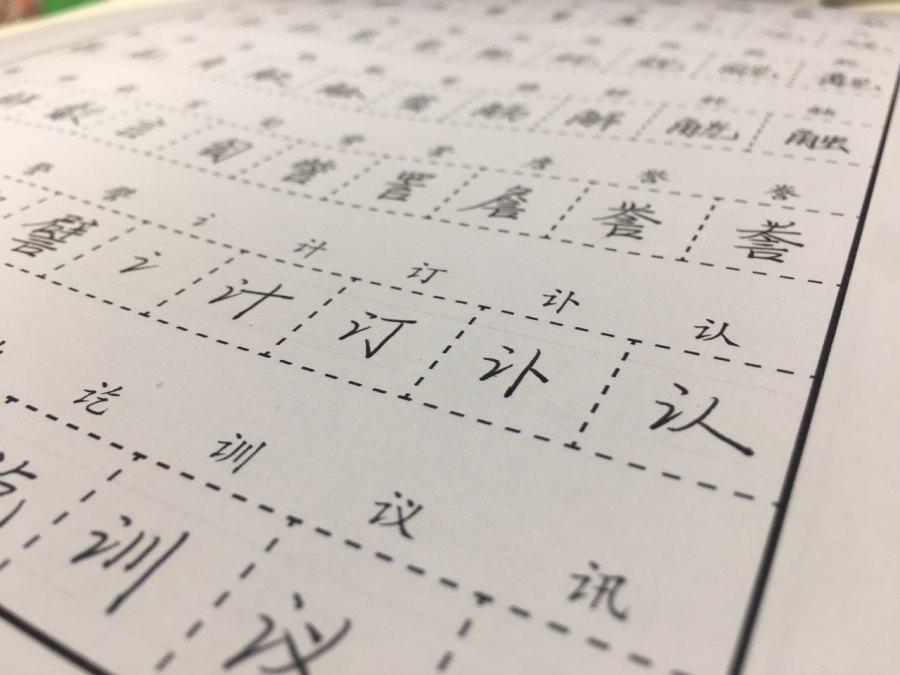
义启年少不知爱这个字体跟它的名字一样让人感觉到有点的硬朗,仿佛就是对爱情懵懵懂懂的状态,还不知道爱情的柔软。他是小编推荐的比较适合女生练的硬笔字体,它的字体比较细所以看起来很干净,很清秀。这样的字体看起来不不是柔柔弱弱的,撇和横都稍微带了点弯弯的曲线,看起来不是特别的生硬,这种字体写起来也不是很难。
X-热血江湖体这个字体也是适合女生练的硬笔字体之一,看看它的名字就知道这个字体不简单,带点江湖气。但是这个字体还是很秀气的,与上面两个不同的是它看起来更有英气一些,比较适合不是特别乖乖女的女孩子,有的女孩子性格比较直率有点像男孩子的性格,他们也不太喜欢太女性化的字体,所以小编推荐的这个字体很适合这个人群。